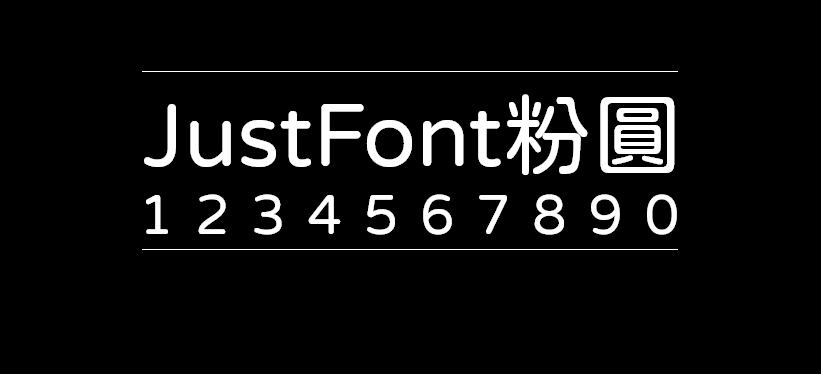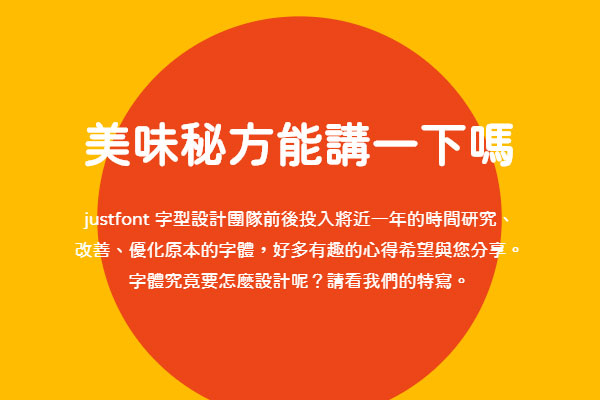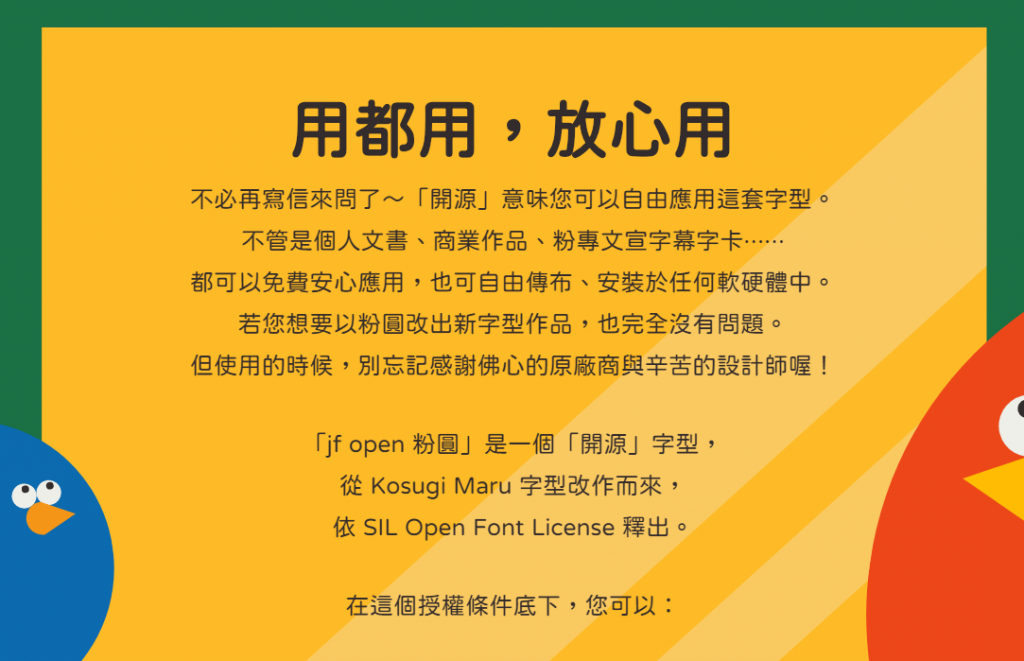
粉圆字体(jf open 粉圓 1.0)是台湾字体公司金萱字型成功后,为回馈社会,承诺为台湾使用者优化一套开源字型作品。 2019年,JustFont 终于提出了“粉圆计划”,将基于现已开源的日本Motoya公司的小杉圆体进行改造、升级成新的开源字型粉圆字体。粉圆字体在原日文字型基础上,额外设计了1,477个中国台湾常用字、注音符号与台罗拼音,并修订排版设定,以适应使用需求。更改进了灰度品质,让排版更美丽! 简单来说,粉圆字体改了什么?粉圆字体做一套适合排版的、品质良好的开源圆体。这包含调整标点符号的位置,新增很多繁体中文会用到的字,还把原本汉字的品质变得更好。
1、小杉圆体中文字体较少,粉圆字体增加了1477个汉字。
2、因为日本的标点符号的习惯与中国不同,所以粉圆字体调整了符号的位置,并把添加正统圆体的特征。
3、修改字体的灰度,让字体达到理想状态。在修改这些字的“灰度”上花了很多时间。原本的字会常常出现部件笔画粗细不一致的现象,那我们就是必须手动去一笔一画的把粗细调整到比较理想的状态。这样一来就不会有些字比较黑,有些字又比较淡。
JustFont粉圆字体是基于Kosugi Maru改作,由JustFont设计师针对台湾日常应用加以优化的开源字型。欢迎大家自由应用、自由优化、自由改作!